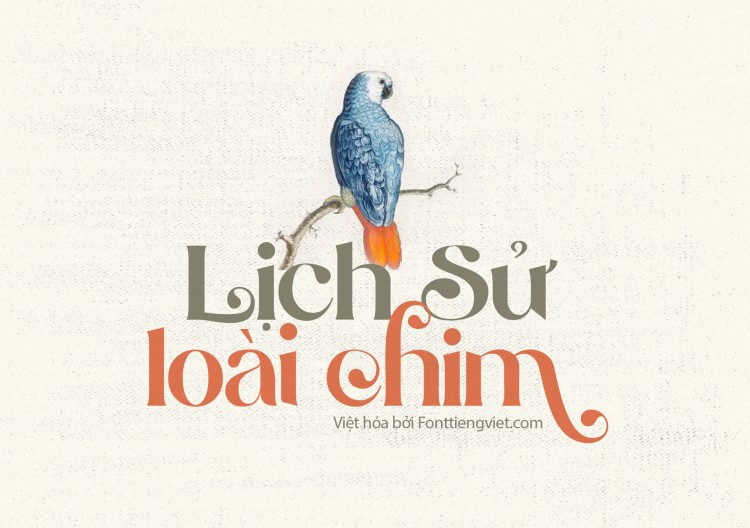
Font việt hóa 1FTV Calgary
Giới thiệu về Font việt hóa 1FTV Calgary
Trong thế giới đồ họa hiện đại, việc lựa chọn Font Miễn Phí phù hợp đóng vai trò then chốt giúp truyền tải thông điệp hiệu quả. Font việt hóa 1FTV Calgary nổi lên như một giải pháp lý tưởng dành cho những ai yêu thích sự kết hợp giữa nét cổ điển và hơi thở đương đại. Đây là bộ phông chữ Serif tinh tế, được đội ngũ 1FTV chỉnh sửa kỹ lưỡng để hỗ trợ đầy đủ bảng mã tiếng Việt, giúp người dùng không còn lo lắng về lỗi hiển thị ký tự khi gõ dấu.
Đặc điểm nổi bật của bộ font
Bộ Font việt hóa 1FTV Calgary sở hữu những đường nét thanh mảnh nhưng vô cùng chắc chắn. Cấu trúc chữ được thiết kế với độ tương phản vừa phải, tạo cảm giác dễ chịu cho mắt người đọc. Đặc biệt, các ký tự được tối ưu hóa khoảng cách, giúp văn bản trở nên chuyên nghiệp và bắt mắt hơn trên cả ấn phẩm in ấn lẫn màn hình kỹ thuật số.
Ứng dụng thực tế của Font việt hóa 1FTV Calgary
Nhờ vẻ ngoài sang trọng, bộ font này thường được ưu tiên sử dụng trong các thiết kế bìa sách, tạp chí thời trang hoặc menu nhà hàng cao cấp. Đối với các bạn học sinh và sinh viên, đây cũng là công cụ tuyệt vời để trình bày bài thuyết trình hoặc làm báo cáo dự án thêm phần ấn tượng.
Lưu ý khi sử dụng trong thiết kế
Khi sử dụng Font việt hóa 1FTV Calgary, bạn nên kết hợp với các tông màu trung tính để làm nổi bật sự thanh lịch. Đừng quên điều chỉnh kích thước chữ phù hợp với bố cục tổng thể để đảm bảo tính thẩm mỹ cao nhất cho sản phẩm của mình.